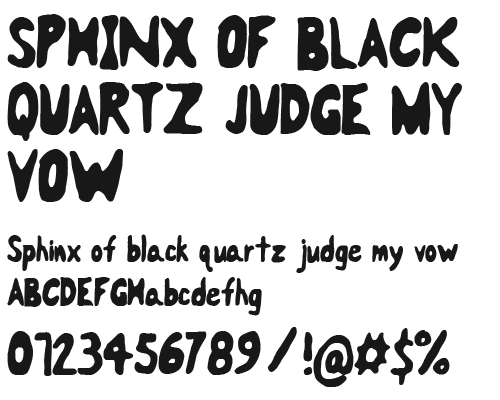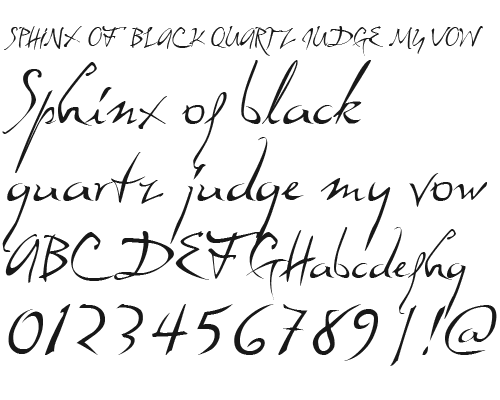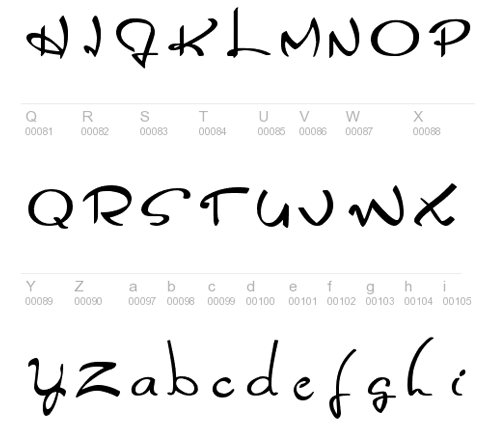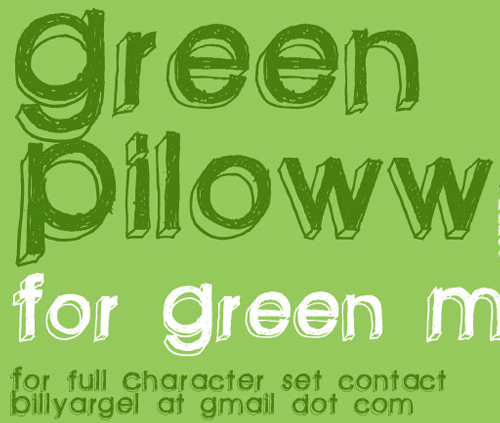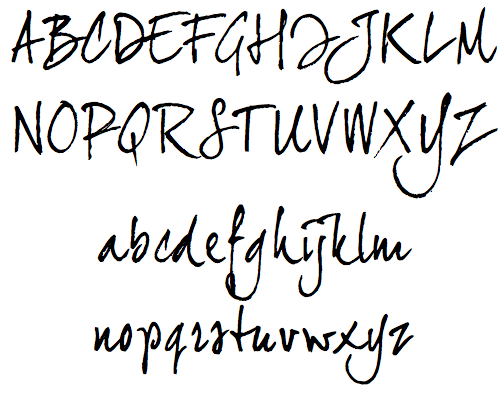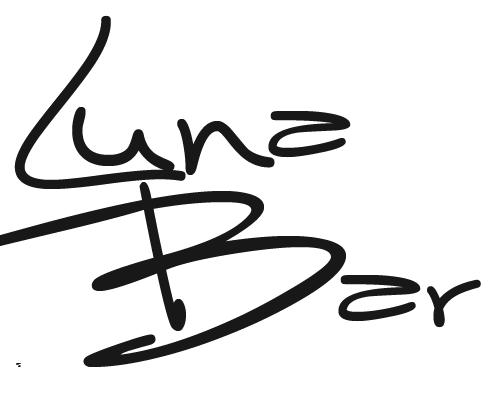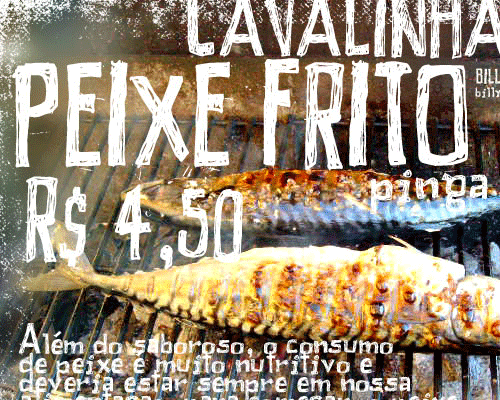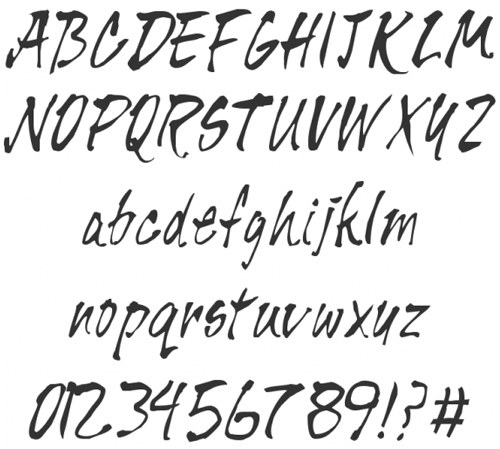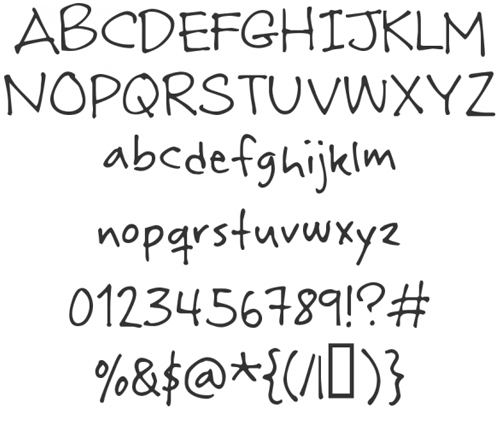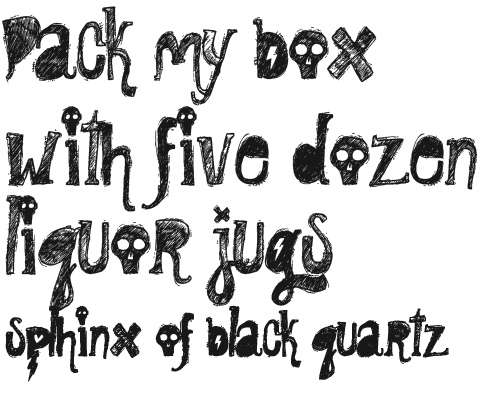
40 бесплатных шрифтов «от руки»
40-прописных-шрифтов В отличии от обычных шрифтов, шрифты “от руки” не смотрятся слишком строго, но они дают возможность лучше контактировать с посетителем сайта. Такие шрифты могут отлично смотреться в дизайне, придать ему определенный стиль и креативный вид. Несколько примеров применения таких шрифтов вы сможете увидеть в  ранее опубликованной подборке 23 художественных сайта.
Шрифт Alpha Mack
Прописные шрифты
Шрифт под названием Analgesics
Наведенный шрифт прописью
Шрифт Bubbly Frog
Жирный прописной шрифт
Шрифт под названием Christopher Hand
Шрифты от руки
Отличный прописной шрифт Dali
Креативный шрифт прописью
Шрифт “от руки” Fabulous 50s
Шрифт с символами различной величины
Обведенный шрифт Fail
Обведенный шрифт
Зарисованный шрифт FFF Tusj
Зарисованный шрифт
Шрифт Daniel
Латинский прописной шрифт
Шрифт под названием Note this
Шрифт прописью
Отличный прописной шрифт Pisan
Отличный прописной шрифт
Шрифт “от руки” Rabiohead
Шрифт “от руки”
Креативный шрифт Glider Girls
Креативный шрифт
Шрифт в стиле гранж Green Piloww
Шрифт в стиле гранж
Шрифт под названием Grutch Shaded
Шрифт с тенью
Жирный прописной шрифт Hand of Sean
Жирный прописной шрифт
Гранжевый шрифт HandVetica
Гранжевый шрифт
Шрифт Jamaistevie
Перечеркнутый шрифт
Прописной шрифт под названием James Fajardo
Прописной шрифт
Креативный шрифт Estrya’s Handwriting
Креативный шрифт
Шрифт “от руки” Jerry’s handwriting
Шрифт “от руки”
Прописной шрифт Joe Hand 2
Прописной шрифт
Аккуратный шрифт Journal
Аккуратный прописной шрифт
Шрифт под названием Just Me Again Down Here
Прописной шрифт
Шрифт Later On
Угловатый шрифт от руки
Жирный шрифт “от руки” Love Ya Like A Sister
Жирный шрифт “от руки”
Шрифт “от руки” с завитками Luna Bar
Шрифт “от руки” с завитками
Наведенный шрифт Mia’s Scribblings
Наведенный шрифт
Креативный шрифт “от руки” Pappo’s Blues Band
Креативный шрифт “от руки”
Наведенный шрифт в стиле гранж Peixe Frito
Наведенный шрифт в стиле гранж
Шрифт Positiv-A
Ровный зарисованный шрифт
Шрифт с черепами Rock Show Whiplash
Шрифт с черепами
Шрифт Salamander
Шрифты от руки
Жирный прописной шрифт Sophie, Regular
Жирный прописной шрифт
Еще один шрифт в стиле гранж The Quiet Scream
Шрифт с потеками и брызгами
Шрифт Thurston Erc
Наведенный гранжевый шрифт
Знаки и буквы различных размеров в шрифте Two Turtle Doves
Шрифт с знаками и буквами различных размеров
Шрифт WC RoughTrad Bta
шрифт в стиле гранж
Креативный прописной шрифт Windsong
Креативный прописной шрифт